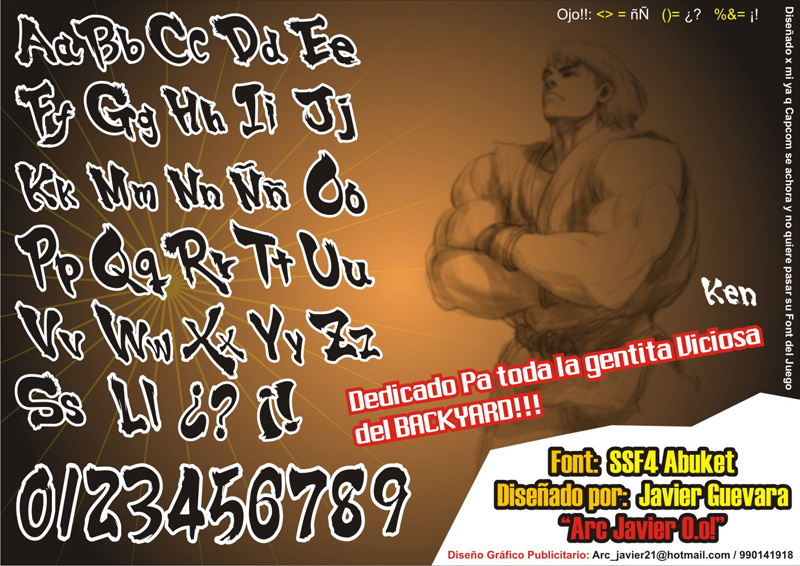
Font name: | SSF4 Abuket |
Author: | ArcJavier |
Primera Font Inspirada en el Juego Super Street Fighter IV Para Uso Personal. Si en caso la necesitan para algún proyecto, o intenta lucrar con ella deberá donar $25 a mi cuenta de PayPal. Font diseñada por: Javier Guevara Valle Rising Art Publicidad Diseñador Gráfico - Fotógrafo Publicitario Javi.guevara21@gmail.com 99014-1918 Pronto la versión Mejorada. |